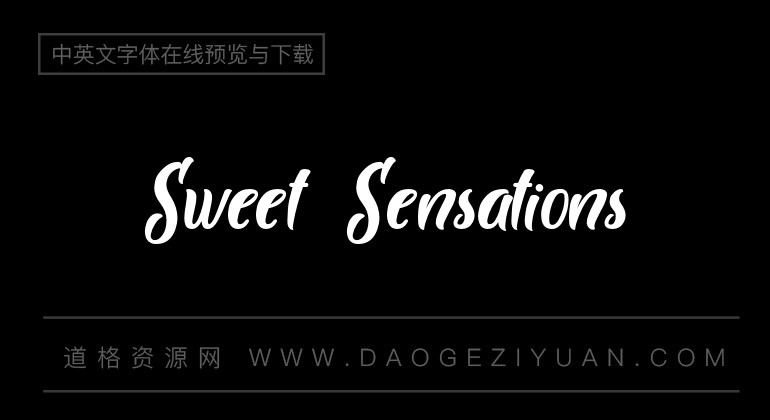
Sweet Sensations
Sweet Sensations 是一款可爱的手写体字体,它具有温暖、浪漫、可爱的特点,适合用于表达爱意和情感。它采用粗细不一的笔触,字形具有柔和的曲线,表达出柔和的感情,可以营造出温馨的氛围。Sweet Sensations 字体适用于浪漫的约会、婚礼、礼品包装等,也可以用于婴儿用品、宠物用品的包装上,让它们看起来更加可爱。
Sweet Sensations是一款非常不错的手写艺术字体,具有很好的视觉感,适合于文化类的宣传设计、商业类品牌的广告和产品包装设计以及个性化文字排版等较多场景。